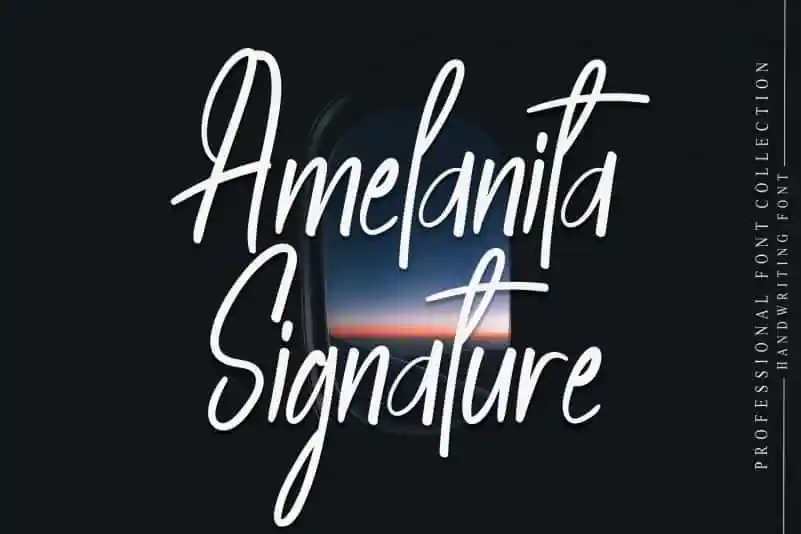
Amelanita Signature Script Font – Fonte Grátis
Amelanita Signature Script Font
A Amelanita Signature Script Font é uma delicada elegância que transborda criatividade para quem busca expressar sua personalidade através das letras escritas à mão. Ela não só oferece um toque de sofisticação aos documentos e design gráfico, mas também cria um ambiente único e envolvente, tornando-se a escolha perfeita para aqueles que valorizam uma fonte única capaz de transmitir expressão e emoção em seus trabalhos. Este é o tipo de fonte ideal para designers buscando criar algo mais pessoal, onde cada traço da letra reflete um pouco do indivíduo que a cria. Com sua tipografia fluida e fluida, a Amelanita Signature Script Font transforma qualquer projeto em um verdadeiro ato de expressão visual. Para os criativos na busca constante por algo novo, essa fonte é uma excelente escolha para dar vida à sua visão única no mundo do design.